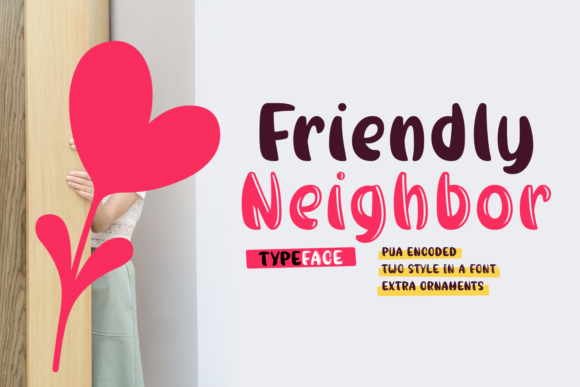
Friendly Neighbor
Friendly Neighbor – Avaliação Completa da Fonte Mais Divertida
Se você está em busca de uma tipografia que una legibilidade impecável e um toque lúdico, a Friendly Neighbor pode ser a escolha perfeita. Disponível em dois estilos exclusivos dentro de um único pacote, esta fonte destaca‑se em projetos que precisam de personalidade sem perder a clareza.
- Dois estilos versáteis: combinações de peso e inclinação que permitem criar hierarquias visuais de forma natural.
- Alta legibilidade: traços arredondados e espaçamento inteligente facilitam a leitura em telas e impressos.
- Design amigável: linhas suaves e formas acolhedoras transmitem simpatia e acessibilidade.
- Doodles inclusos: um conjunto de ilustrações divertidas para enriquecer layouts, banners e materiais de marketing.
Por que usar a Friendly Neighbor?
Esta tipografia é ideal para:
- Identidades de marcas infantis ou voltadas para o público familiar.
- Campanhas publicitárias que buscam um ar descontraído e próximo do consumidor.
- Materiais educativos, como livros, cartazes e infográficos.
- Websites, landing pages e newsletters que precisam de destaque sem sacrificar a leitura.
Experiência de Uso
Ao testar a Friendly Neighbor em projetos reais, percebi que a combinação dos dois estilos permite criar contraste visual sem recorrer a fontes adicionais. Os doodles incluídos são vetores de alta qualidade, prontos para serem escalados e coloridos, o que economiza tempo e eleva o nível criativo das peças.
Em resumo, Friendly Neighbor entrega tudo o que um designer procura em uma fonte moderna: legibilidade, personalidade e recursos extras. Se a sua meta é adicionar um toque divertido e acolhedor ao seu design, esta fonte certamente vai elevar o padrão dos seus projetos.